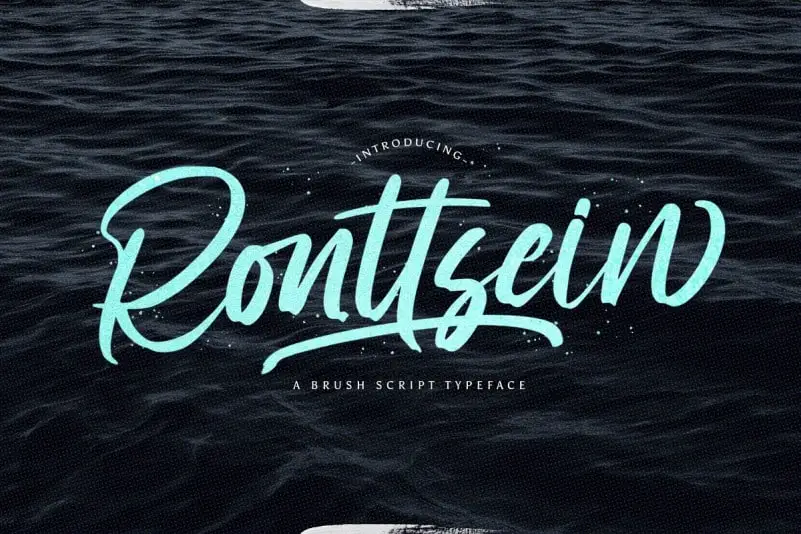
Ronttsein Script Font – Fonte Grátis
Ronttsein Script Font
A Ronttsein Script Font é uma elegante tipografia script desenvolvida por StringLabs para designers que buscam dar vida a seus projetos digitais com um toque refinado e moderno. Inspirada nas características de letras perfeitas, esta fonte apresenta linhas macias e texturas suaves, criando harmonia visual que atende a uma ampla gama de necessidades. Seja para incorporar em logos, criação de estandarte, design de marca ou até mesmo para personalizar anúncios e campanhas de marketing, a Ronttsein traz uma paleta única e sofisticada ao seu trabalho. Combinar linhas sutis com um tom suave e arredondado, esta fonte oferece uma conexão instantânea entre o design visual e a experiência do leitor, tornando-a uma escolha valiosa para qualquer projeto que exija elegância e criatividade.